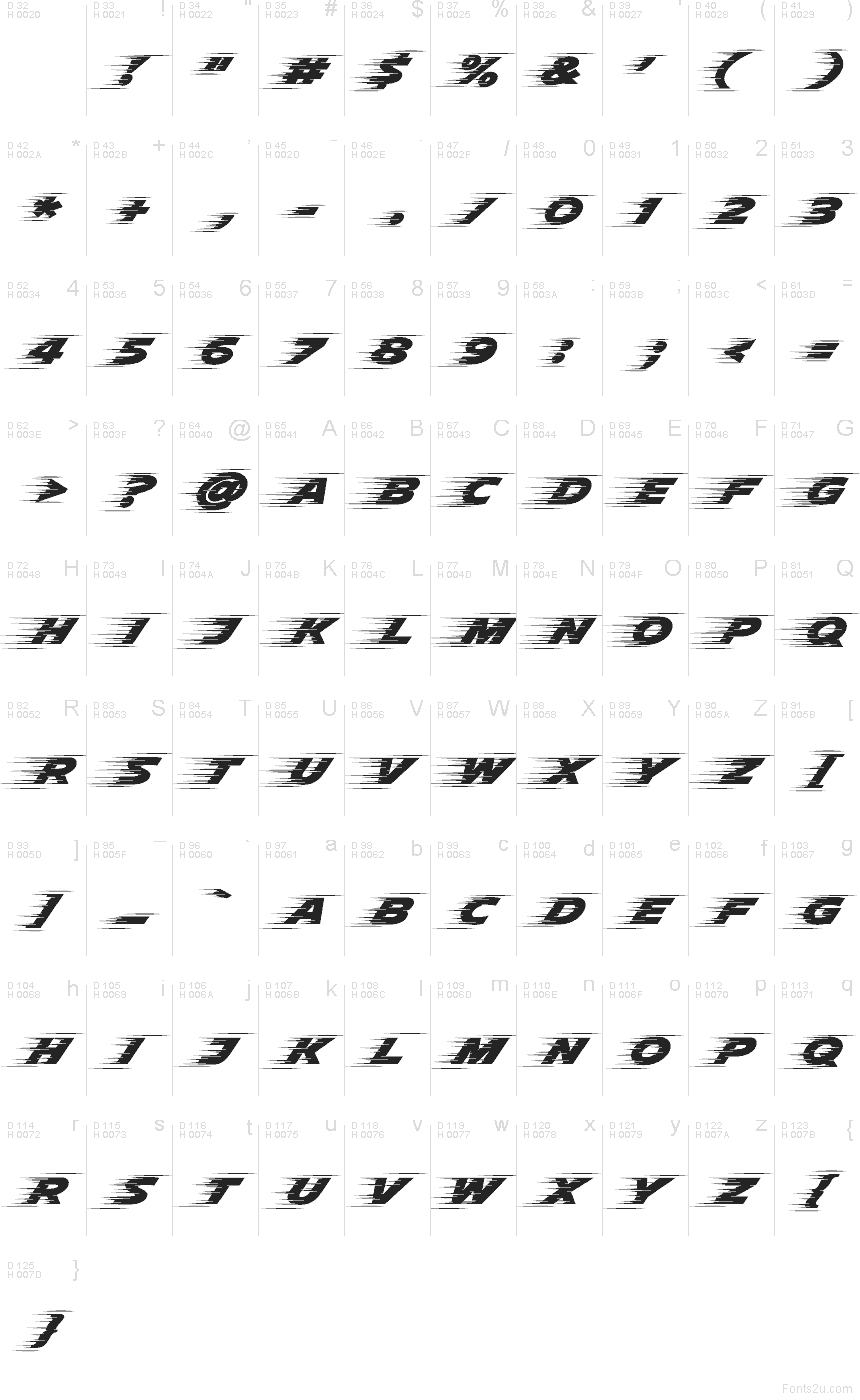
Braaap-S2
Braaap-S2, créée par Youssef Habchi, est une police d'affichage gratuite aux formes inclinées et massives, traversées par des traits horizontaux tranchants et des lignes de mouvement fragmentées. Ces entailles répétées sur chaque caractère lui confèrent une allure rapide et aérienne, tout en conservant la structure solide et compacte des lettres.
Braaap-S2 est idéale pour les affiches de course, les visuels sportifs, les titres dynamiques, les bannières de jeux et la signalétique événementielle audacieuse où la vitesse doit être perceptible au premier coup d'œil. Cette police gratuite est également parfaite pour les autocollants, les logos et les textes promotionnels courts lorsque vous souhaitez que la typographie elle-même véhicule une sensation de mouvement.